今日はふと、
「手書きって、なんだかいいなぁ」って思った気持ちを
書いてみました🧸💭
💌心が伝わる「ぬくもり」がある
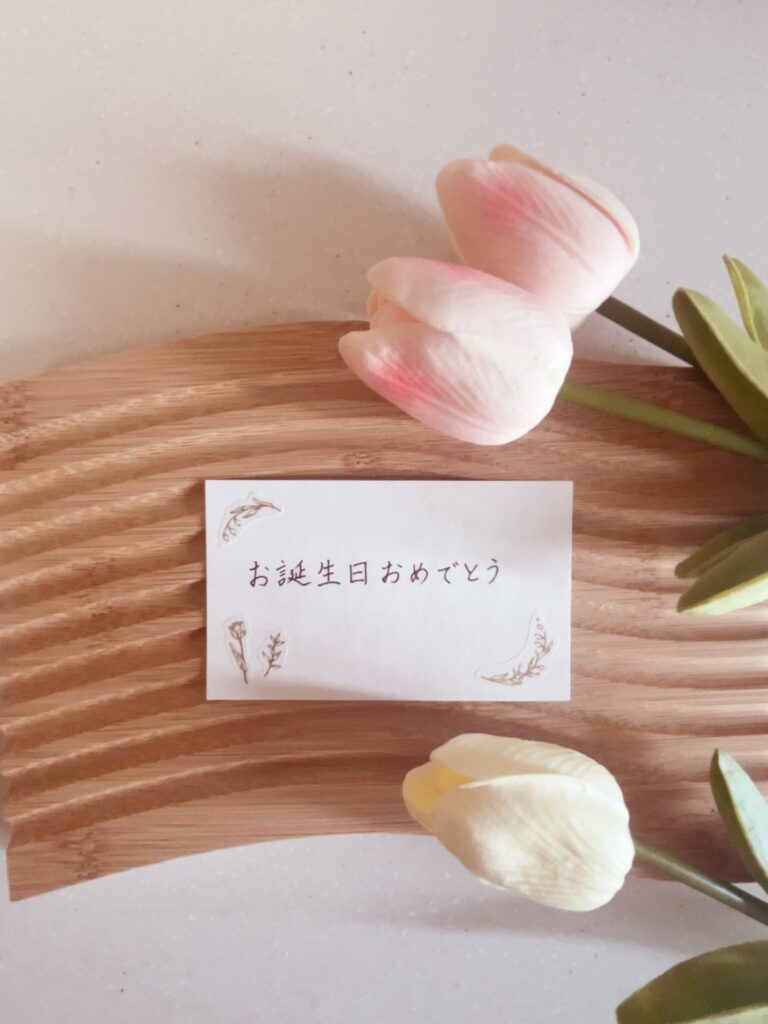
パソコンやスマホで簡単にメッセージを送れる今の時代。
でも、手書きの文字には“その人らしさ”が ぎゅっと詰まっていると思いませんか?🖊💕
たとえば、お礼のお手紙やメモを手書きで もらったとき、
「時間を使ってくれたんだなぁ」って、 心がほっこりした経験…ありますよね☺️💓
そんな“ぬくもり”が、手書きならではの魅力だと思います🌷
📖「ゆっくり書く時間」が、自分を整える
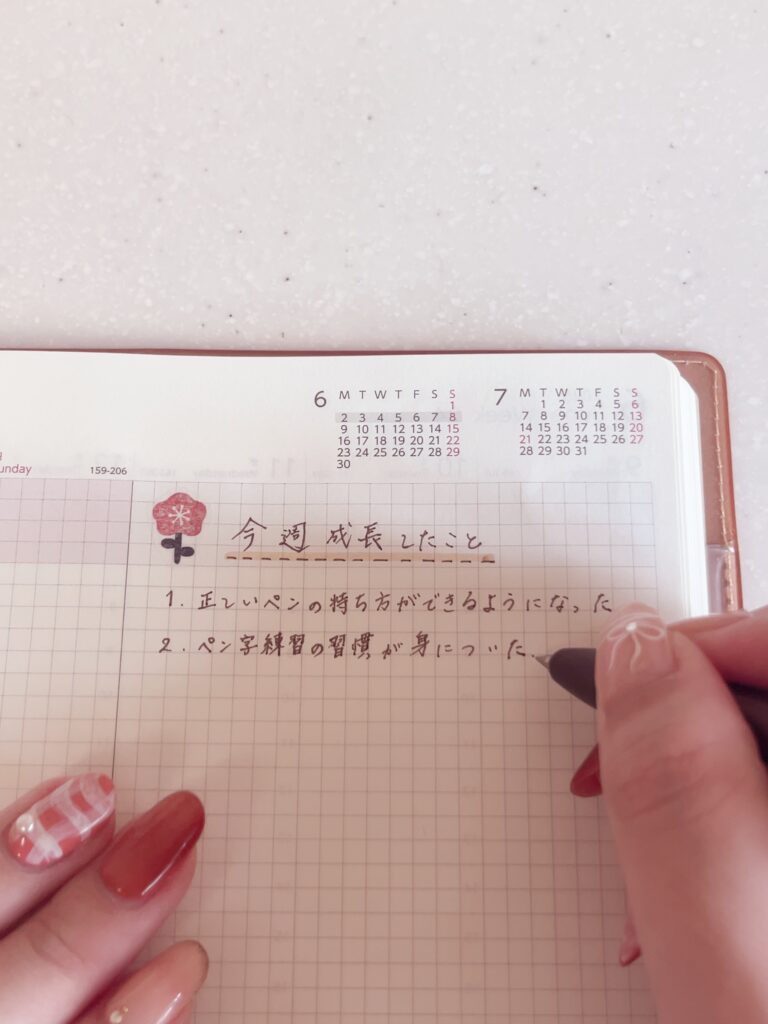
手を動かして、ゆっくり文字を書く時間って、
実はすごく“癒し”になるんです🕊💫
お気に入りのペンとノートを用意して、
今日のこと、ふと思ったこと、
ひと文字ひと文字に気持ちをこめてみる。
忙しい日常の中で、ほっと深呼吸できる
“小さなリセットタイム”になります🍃✨
✏️さいごに
美文字を目指す中で、
どうしても「上手に書かなきゃ…!」って
プレッシャーを感じるときもあるけど、
初心を思い出してみてください🌼✨
手書きって、
人に想いを届けたり、自分を整えるための
とっても優しいツールなんです💐💌
これからも一緒に、
“手書きを楽しむ”こと、大切にしていきましょうね🖊💕